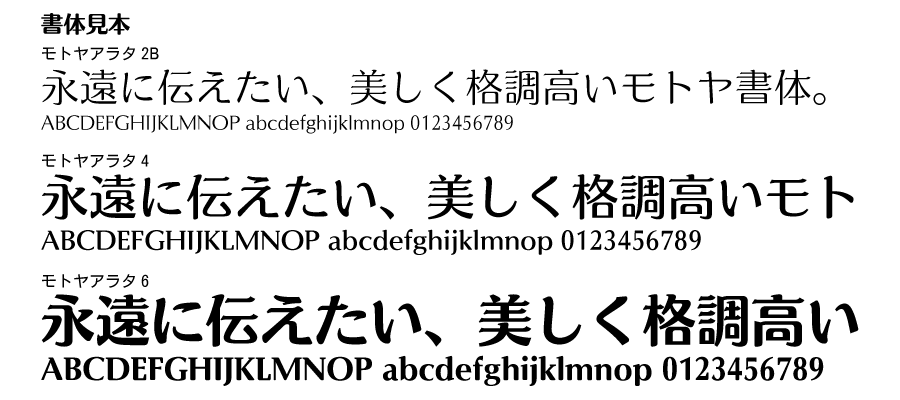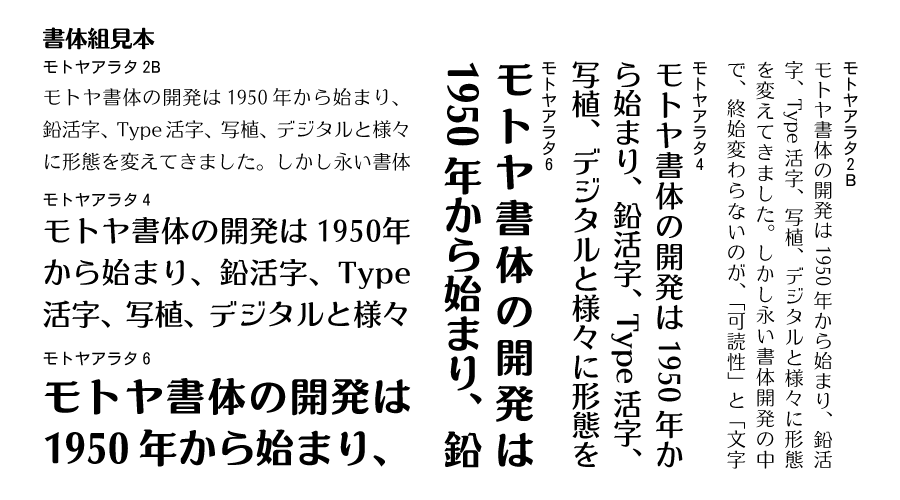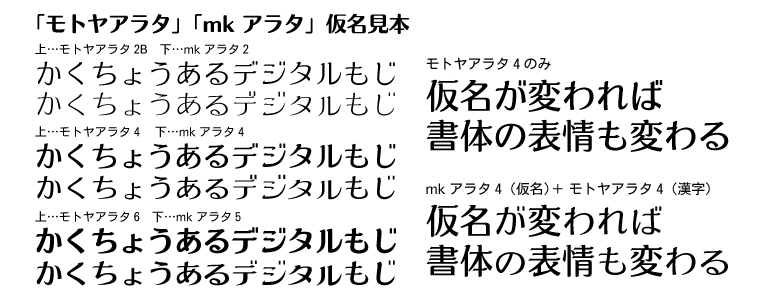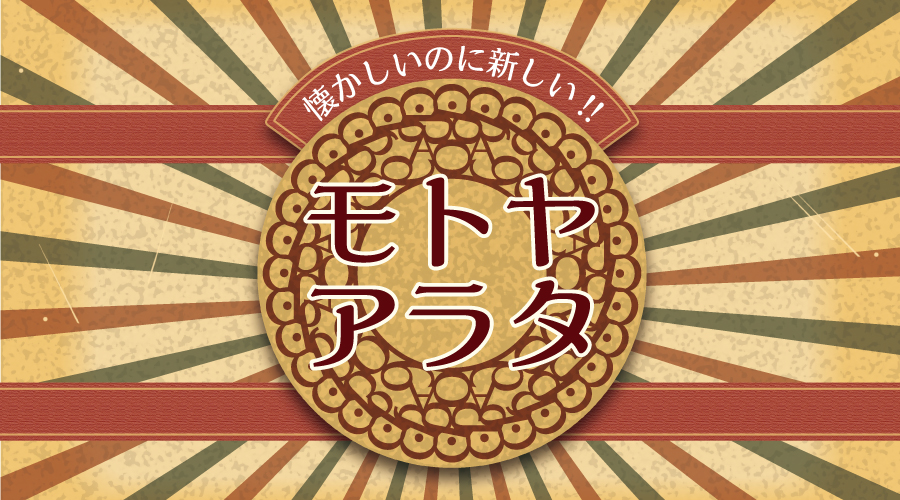
株式会社モトヤは6月15日に新書体「アラタ2B/4/6」の発売を発表した。アラタは元々、金属活字の仮名書体として誕生した書体で、従来のアラタでは仮名のみで文章組みされることが多かく、肩線仮名と呼ばれる欧文書体のようなラインが設定されていた。
今回、和文書体として新発売される「アラタ2B/4/6」では、漢字との混植使用も視野に入れ仮名のデザインを見直し、「懐かしいのに新しい」幅広い分野で活用できる「新たなアラタ」になっている。
従来のアラタが持つエレメントの形状や丸みをはじめ、ゆったりとした「ふところ」などの特徴を漢字のデザインにも取り入れ、アラタのイメージを崩すことなく様々な文章を組めるようになった。漢字と仮名の各種エレメントに統一性を持たせることで、漢字と仮名の調和性が高くしている。